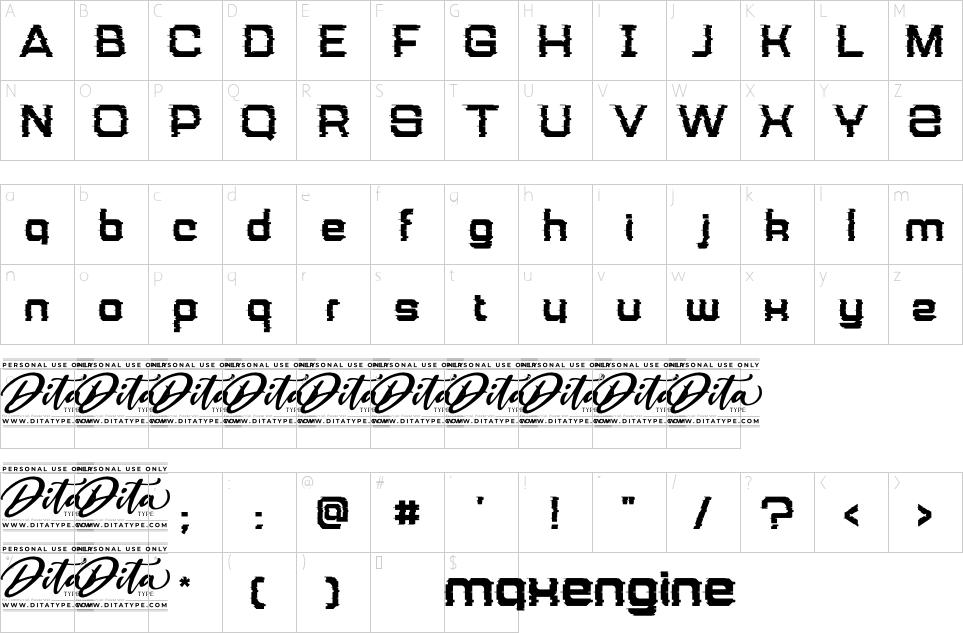
Descubra a fonte Maxengine, uma elegante e moderna opção para seu próximo projeto. Desenvolvida pela Dita Type, essa fonte pode ser usada em ambientes Windows e Mac. Com 831 downloads, Maxengine é uma escolha confiável para designers que procuram uma fonte grata para seus trabalhos. Seja para criar headlines impactantes ou subtítulos legíveis, Maxengine oferece um conjunto de caracteres atraente e personalizável. Sem dúvida, é uma fonte que merece ser adicionada a seu arsenal de recursos gráficos.